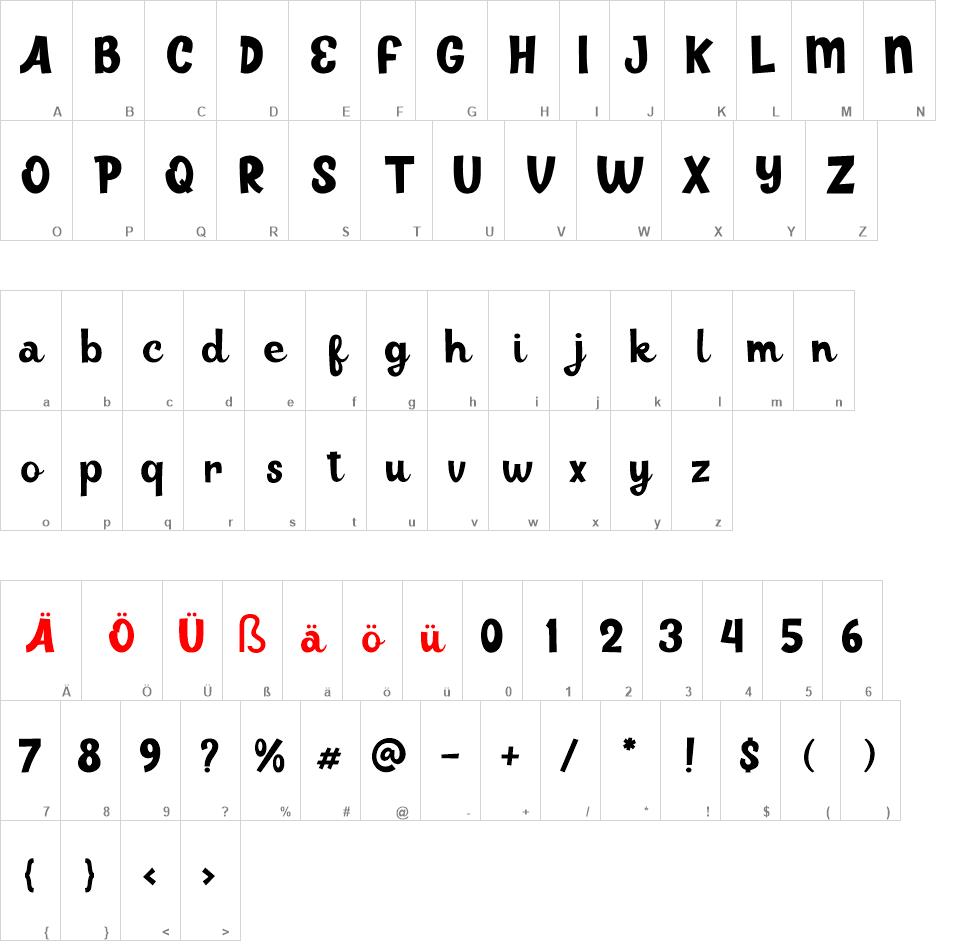
Juiceline
Juiceline  font
Juiceline
Juiceline ist eine fett gedruckte Schriftart mit Umriss- und Schattenschriftarten. Die Schriftart ist mit Opentype-Funktionen ausgestattet. Dazu gehören alternative Zeichen wie: kontextabhängige Alternativen, stilistische Alternativen und Swash-Varianten.